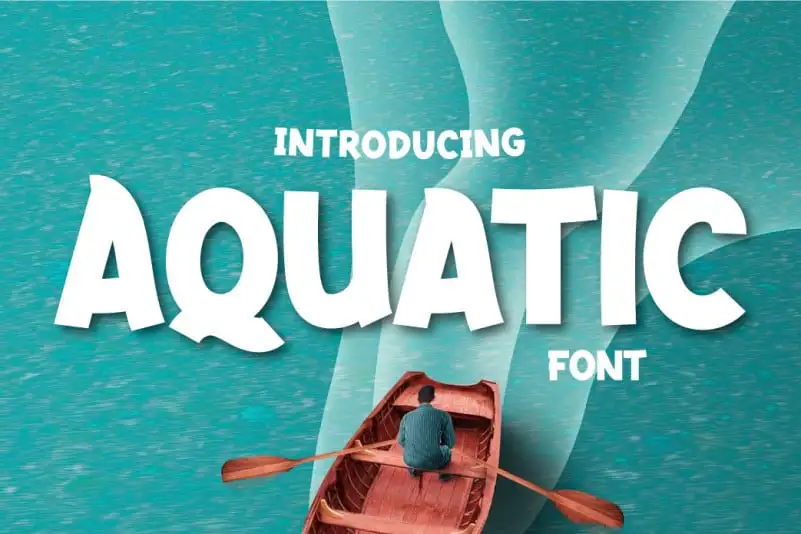
A Aquatic Display Font é uma escolha perfeita para designers buscando algo atraente e versátil no novo desenho da categoria Sans Serif. Este tipo foi projetado com características elegantes e flexíveis, que oferecem um visual sólido, claro e robusto em suas diversas aplicações. Seu uso cria uma aparência bela quando você equilibra-o nas suas próximas obras de arte e projetos gráficos. Com seu design bold, sólido e limpo, a Aquatic Display Font é um elemento perfeito para seus trabalhos, adicionando uma sensação vibrante e ativa à sua obra.